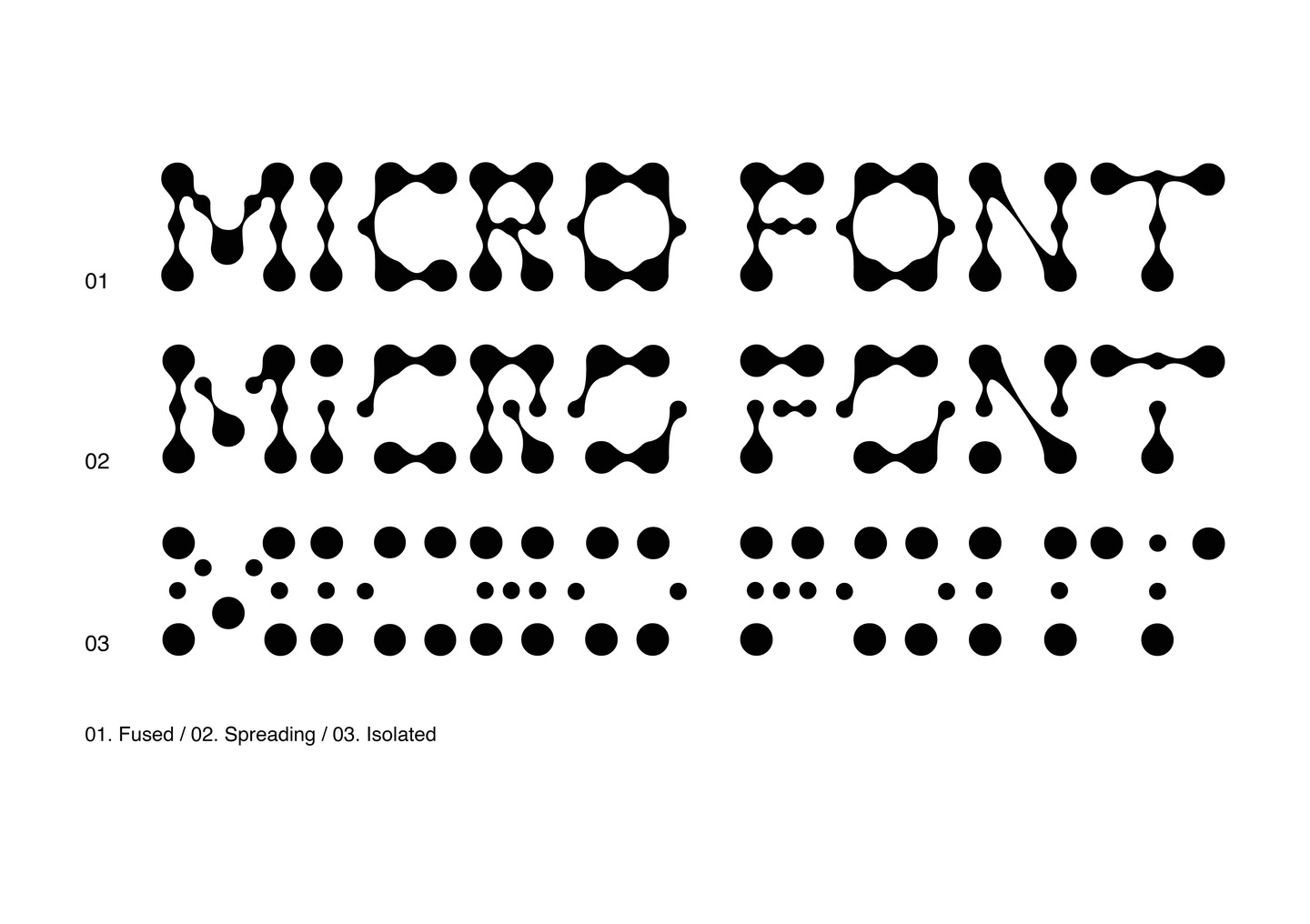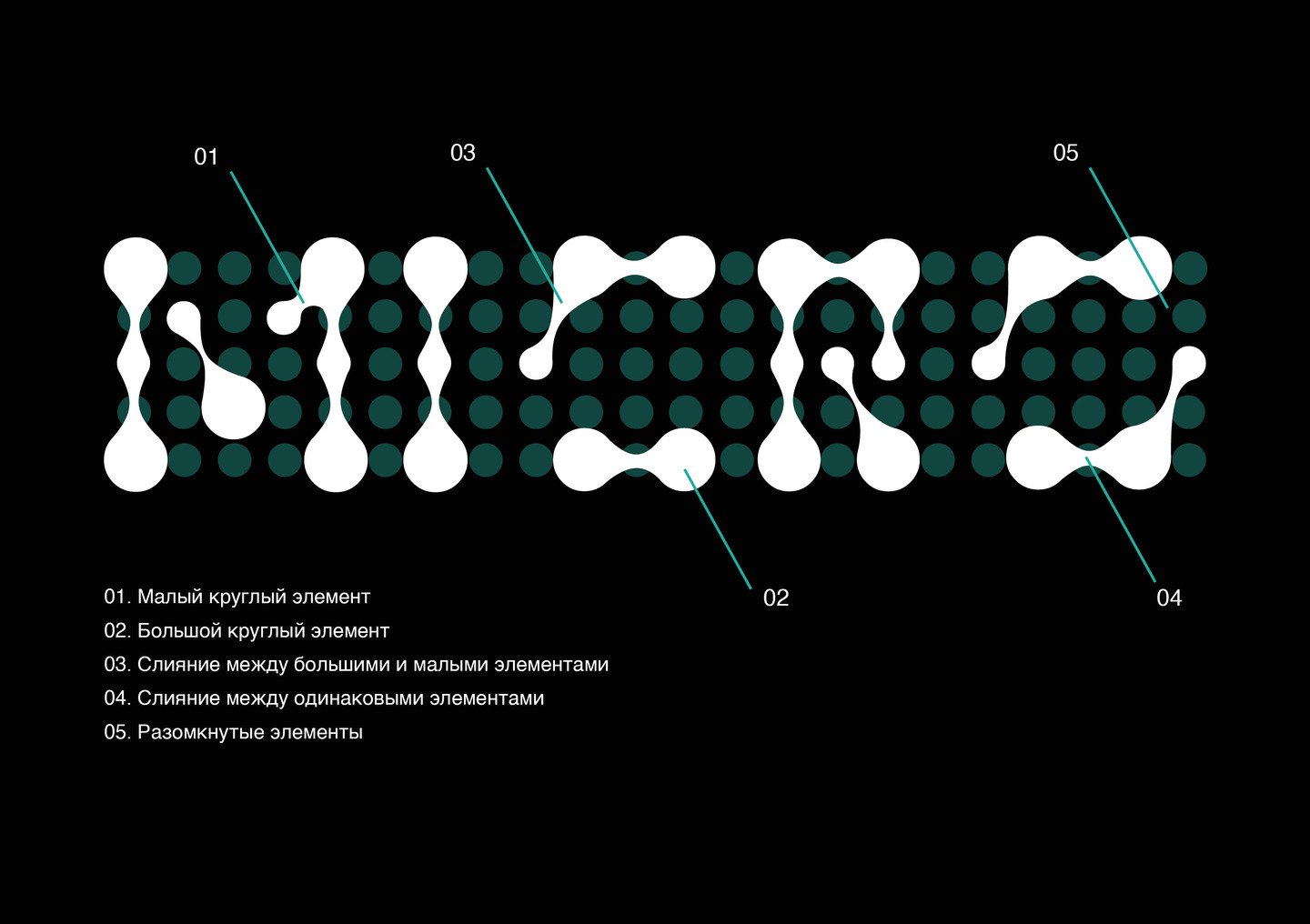
Акцидентный шрифт «MICRO»
Шрифт представляет собой визуальную метафору деления клетки. Каждая буква — живая точечная структура, отсылающая к процессу митоза на микроскопическом уровне. Начертания отражают разные стадии соединения элементов: от отдельных точек до цельных связных форм, превращая типографику в образ роста целой экосистемы
КИРИЛЛИЦА
ЛАТИНИЦА
ЦИФРЫ / ЗНАКИ